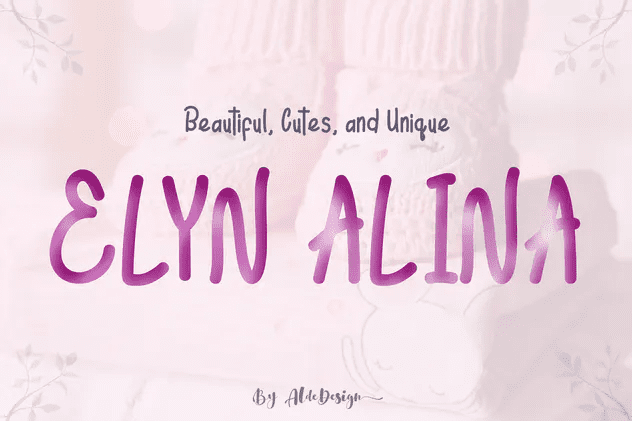
[Creativefabrica] Elyn Alina Font
Название: Elyn Alina Font
[Creativefabrica] Elyn Alina Font
Элин Алина - это теплый рукописный шрифт.
Дизайн шрифта выглядит простым, не теряя своей элегантности и теплоты.
Его функция заключается в том, чтобы показать, что вы обладаете современным духом, чтобы обслуживать высококачественные продукты и услуги.